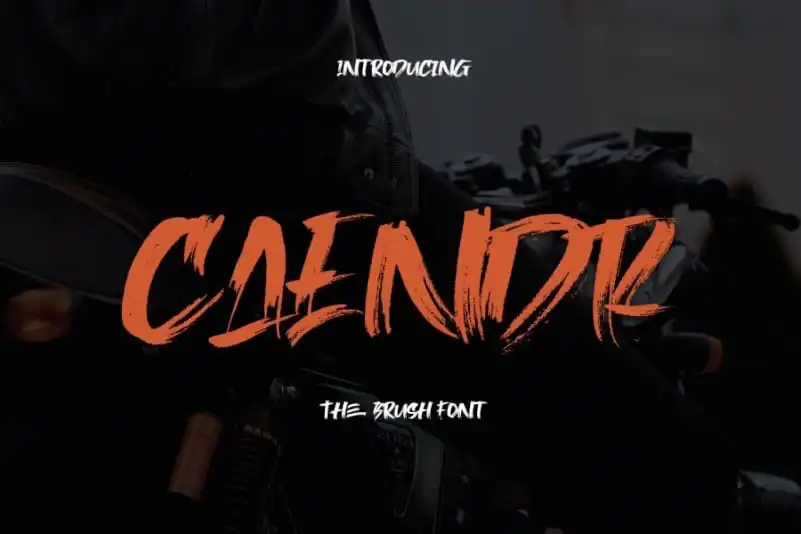
Caendr Brush Font – Download Grátis
A Caendr Brush Font é uma elegante tipografia criada com a técnica do traçado à mão utilizando uma ferramenta desbotada, proporcionando um toque delicado e personalizado. O resultado é um conjunto de letras maiúsculas, perfeitamente feitos por Rometheme Studio, que adicionam sofisticação aos projetos digitais mais variados. Perfeita para criações de moda, designs de roupas, símbolos de marca, capas de álbuns e identidade visual, a Caendr Brush Font também é uma escolha ótima para outras aplicações gráficas onde um touch personalizado seja desejado. É ideal para anúncios, campanhas e redes sociais, trazendo o seu design único às suas criações digitais.